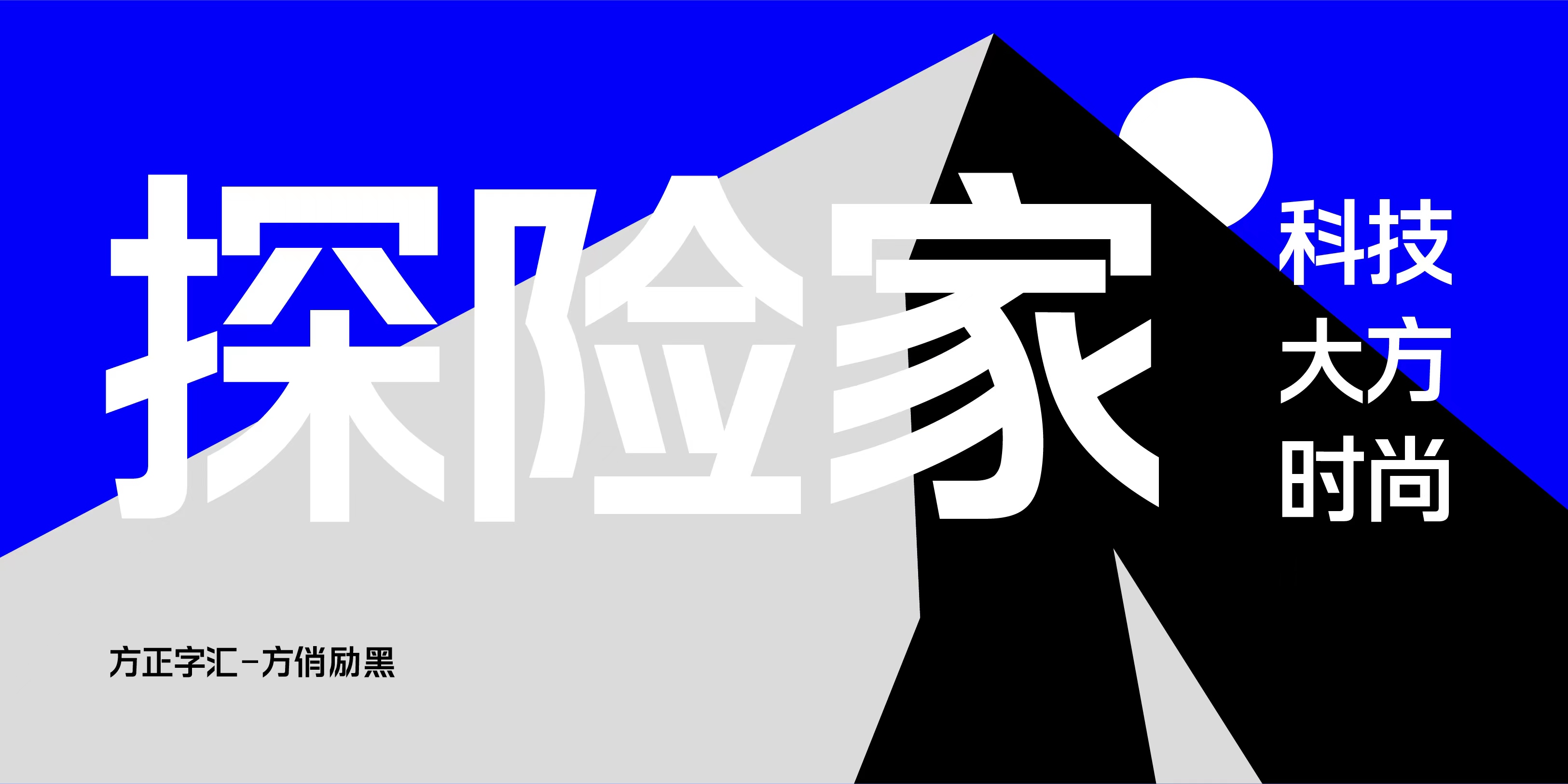
方正字汇-方俏励黑
方俏励黑是一款笔画整齐划一、简约硬朗、科技时尚的字库产品。在常规黑体字的笔画间架里,注入新的视觉设计。字形的起笔和收笔处,采用了大量的横切和竖切处理,部分笔画设计成连笔状态,让文字笔画在视觉上更简约、空间分布更均匀。
适用于品牌中文标志、企业推广语、屏显字幕、包装推广、报纸杂志、影视画面、新媒体、科技广告、电商推广等视觉画面中。